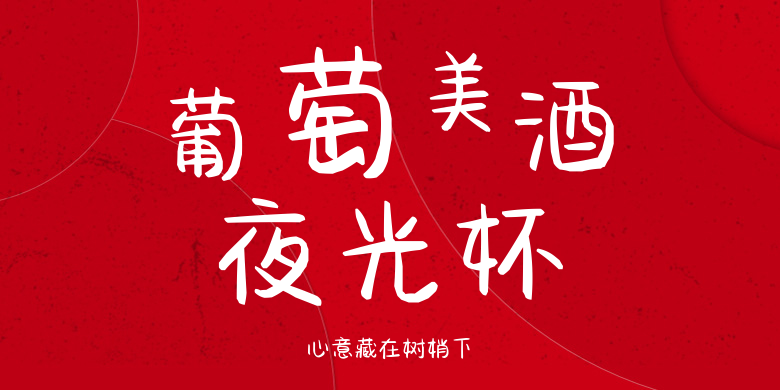
心意藏在树梢下
心意藏在树梢下,这款字体结构工整、笔画清晰,兼顾美观与易读性,适用于标题、正文、海报、包装、LOGO 等多种场景。字形优雅稳定,风格百搭耐看,适配日常排版与创意设计,让文字呈现更舒适、更具质感。心意藏在树梢下一笔一画,皆是细节,以均衡的比例、流畅的线条打造舒适视觉体验,字形端正大气,风格简约现代。无论是商业设计、品牌宣传还是日常排版,都能轻松驾驭,让文字更有格调与力量。心意藏在树梢下字体下载。